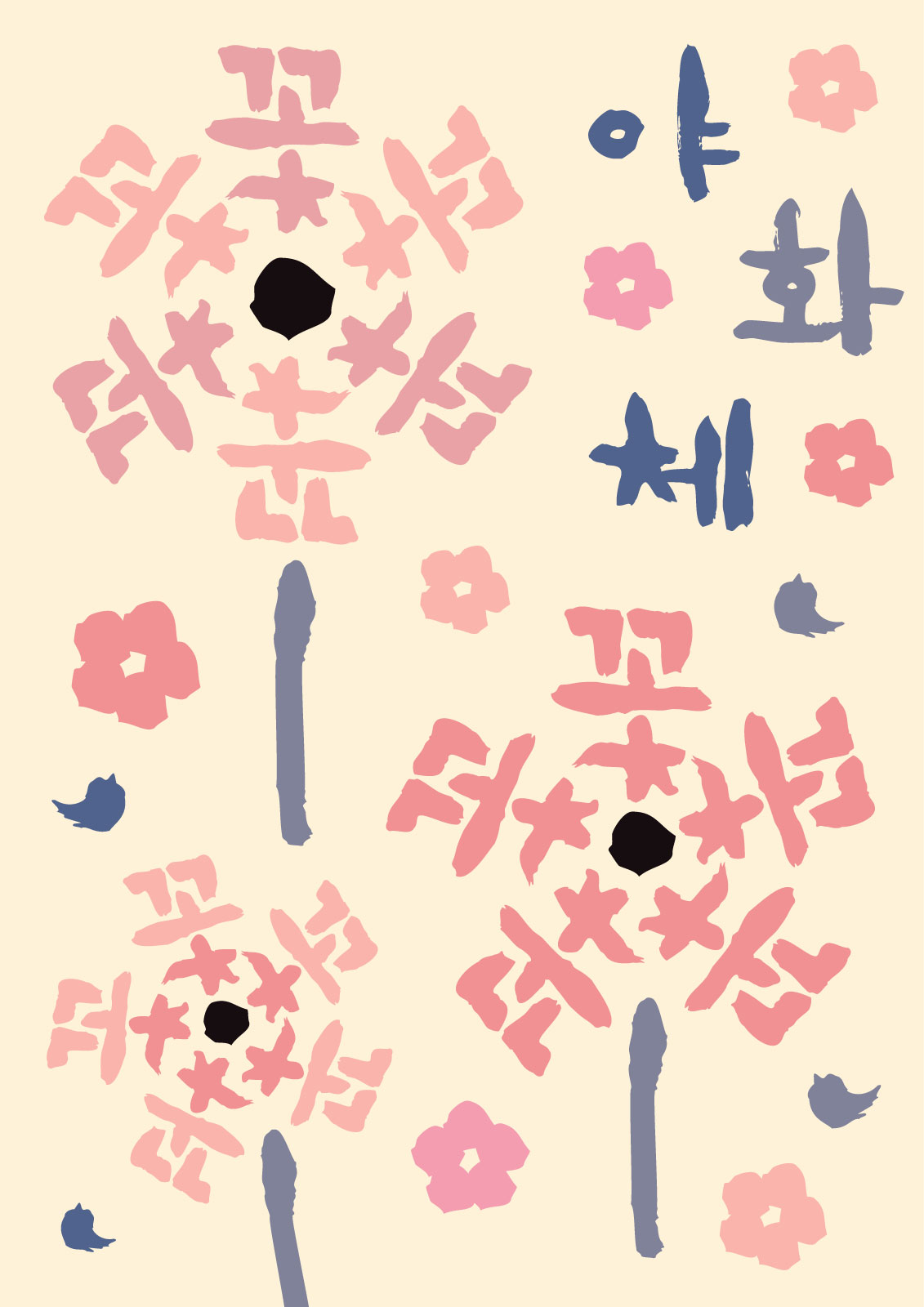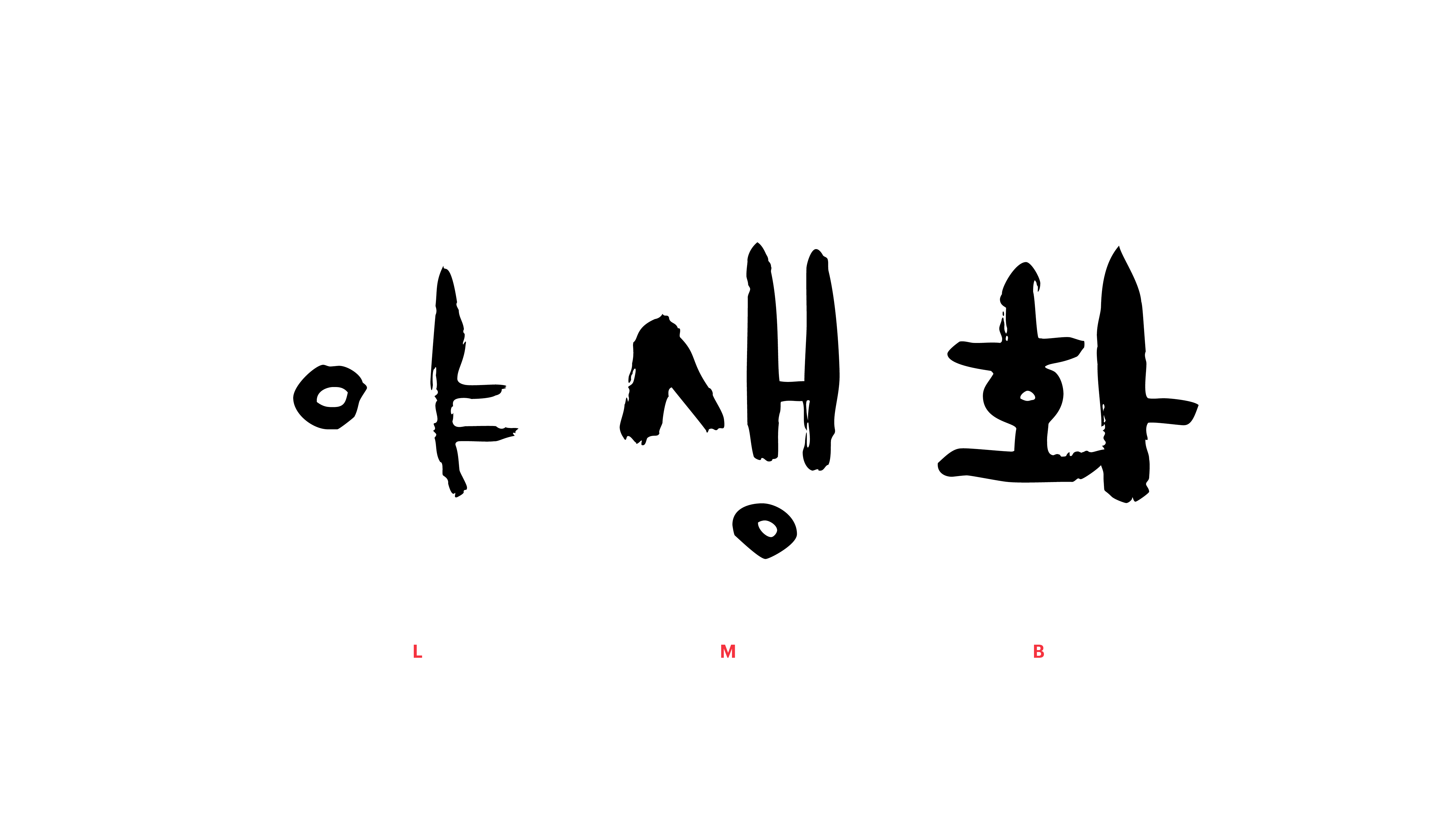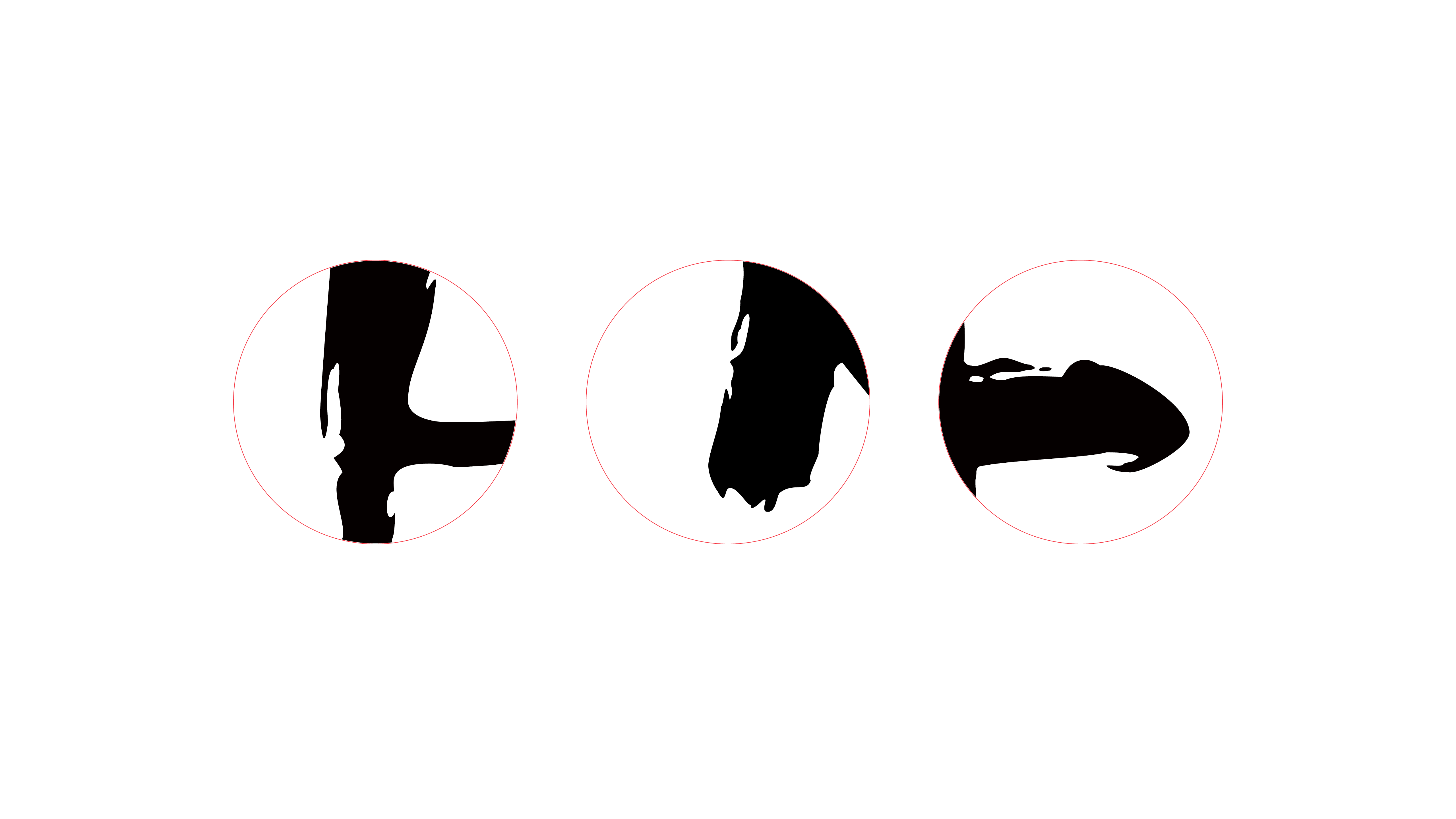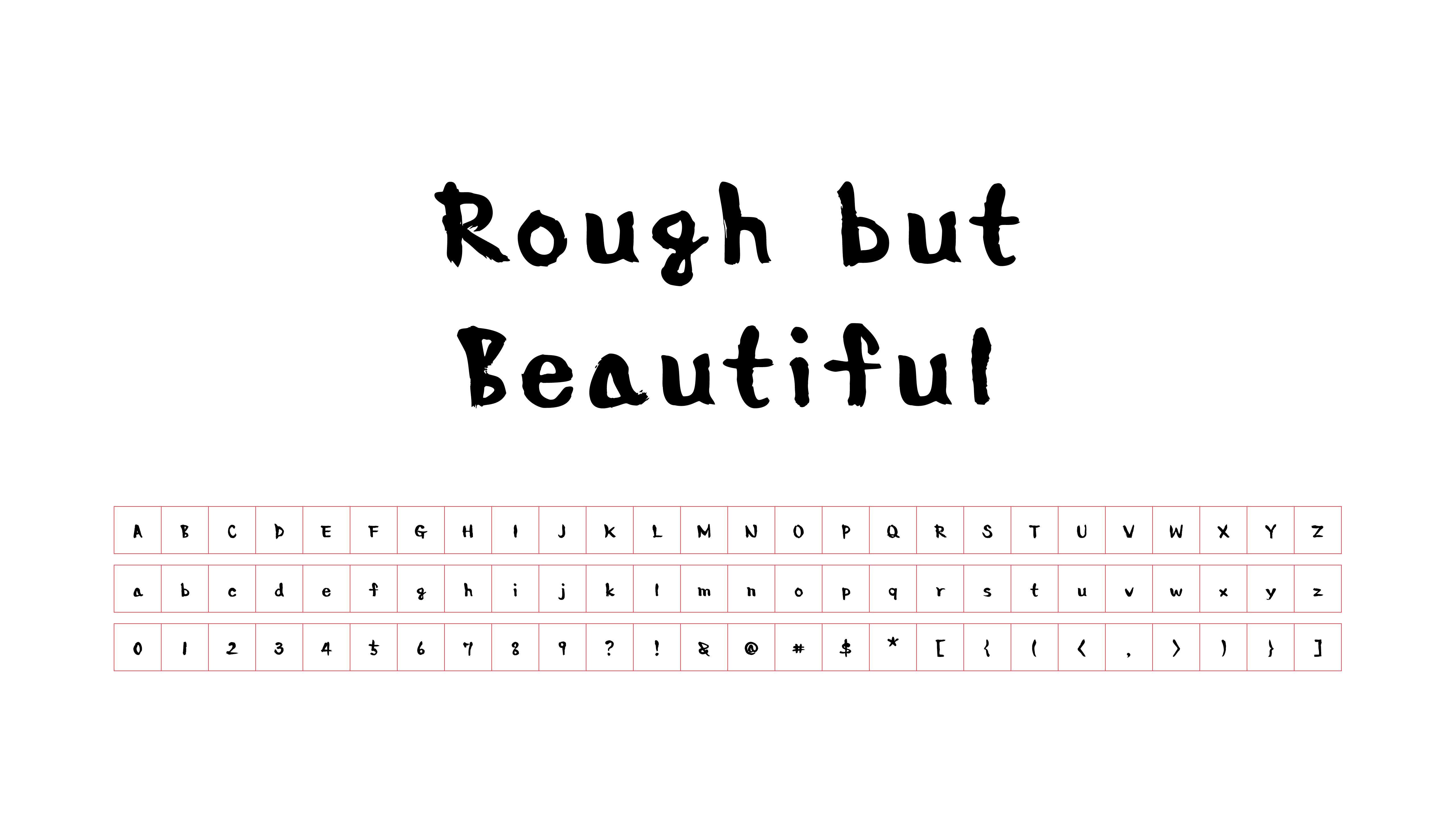
들판에 핀 야생화처럼 거칠지만 소박한 아름다움을 전하는 폰트입니다. 붓글씨를 현대적으로 재해석한 폰트답게 갈필*의 붓 터치로부터 자연스러운 감성이 배어나오도록 신경 썼어요. 자유분방하고 개방적이지만 깊이 있는 아름다움을 표현하고 싶은 날, 한 송이 꽃과 같이 피어 있는 이 폰트에 주목해주세요. *갈필(渴筆) : 물기가 거의 없는 붓에 먹을 묻혀 칠하는 기법. 붓의 질감을 그대로 살릴 수 있다.
Yoon 야화